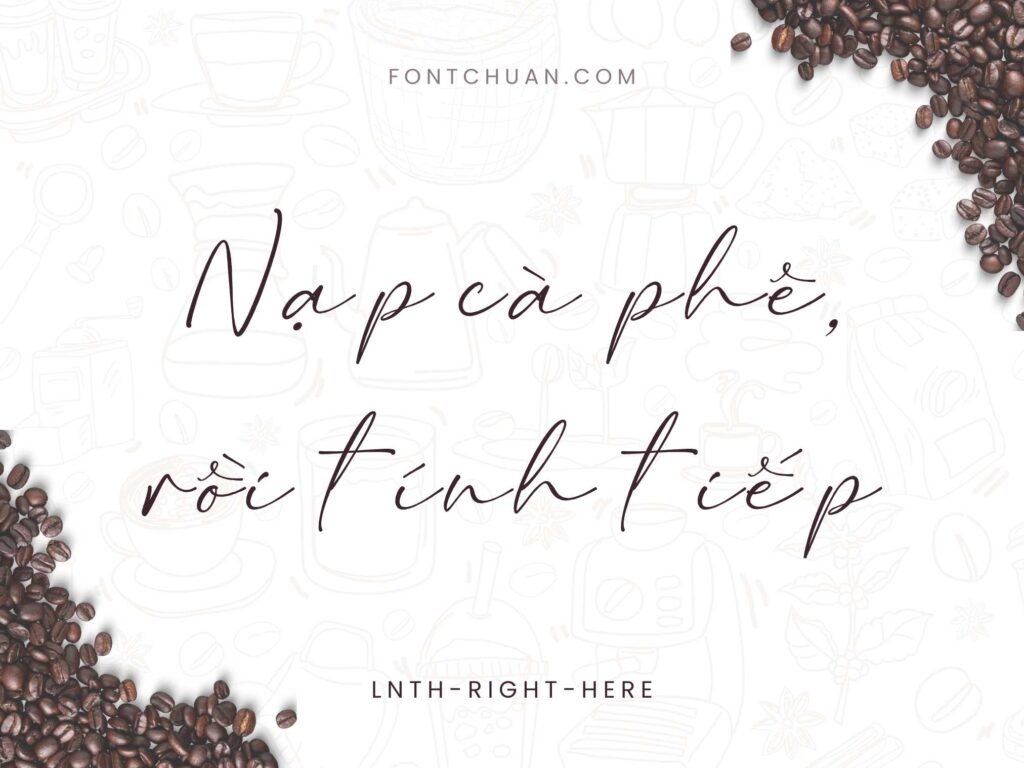
Font LNTH Right Here Việt Hóa
Tác giả Font: Nowhere. Std
Font Right Here là một kiểu chữ viết tay hiện đại, mang phong cách tự do, phóng khoáng nhưng vẫn đảm bảo tính thẩm mỹ cao. Được thiết kế với các nét chữ mềm mại, nhẹ nhàng, font này mang lại cảm giác gần gũi, thân thiện và rất phù hợp cho các dự án sáng tạo, typography nghệ thuật, thiệp mời hoặc thương hiệu cá nhân
Phiên bản này đã được Việt hóa bởi LNTH, hỗ trợ đầy đủ tiếng Việt cùng hơn 50 ngôn ngữ khác, giúp người dùng dễ dàng ứng dụng trong thiết kế quốc tế. Font Right Here được các thành viên Font Chuẩn sưu tầm và đăng tải nhằm cung cấp một lựa chọn hoàn hảo cho những ai yêu thích kiểu chữ viết tay tự nhiên, phá cách
Về đặc điểm thiết kế, Right Here có đường nét thanh mảnh nhưng vẫn rõ ràng, giúp tạo cảm giác nhẹ nhàng, tự do. Kiểu chữ này rất phù hợp để sử dụng trong các thiết kế branding, logo, bao bì sản phẩm, nhãn dán hoặc typography nghệ thuật
Font Right Here được ứng dụng rộng rãi trong các sự kiện như Valentine, Thiệp cưới, Sinh nhật, Trung thu, Giáng sinh. Nó phù hợp với nhiều ngành nghề như quảng cáo, spa, ẩm thực, giáo dục